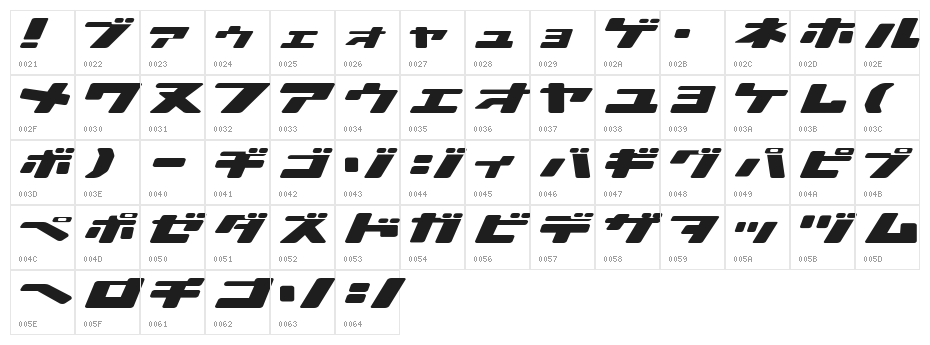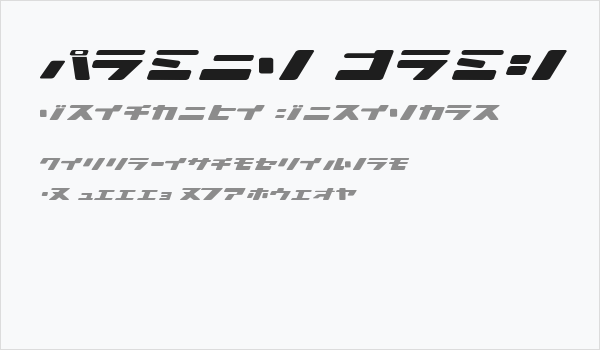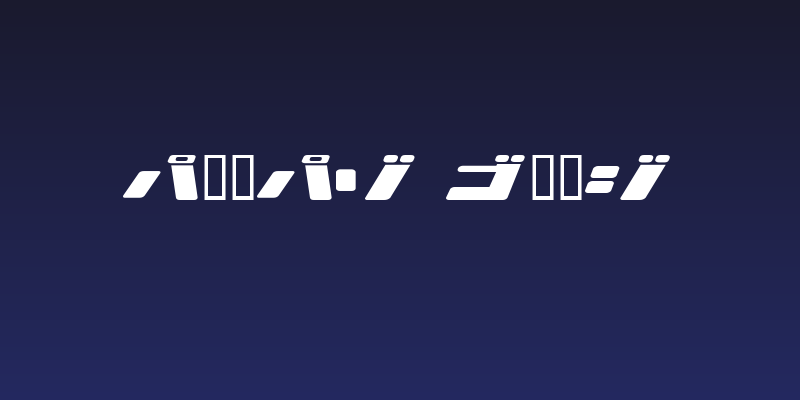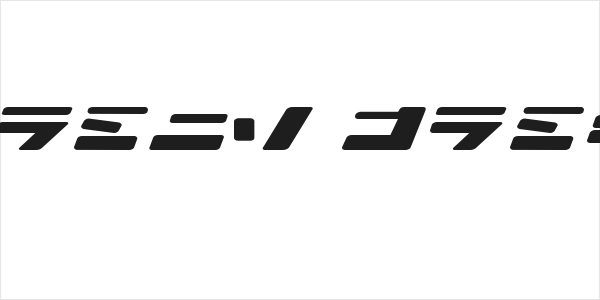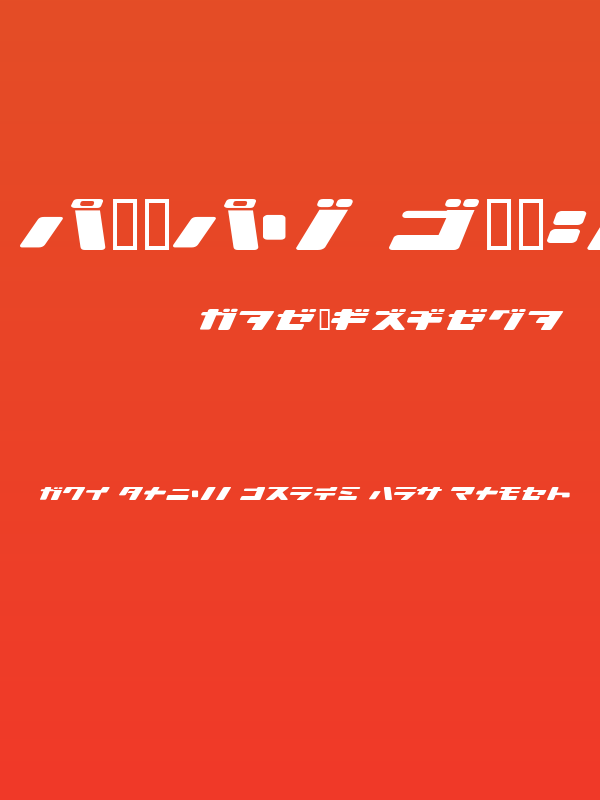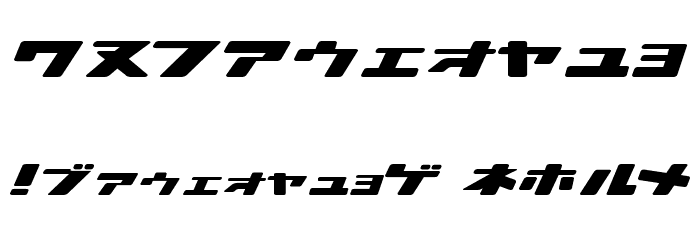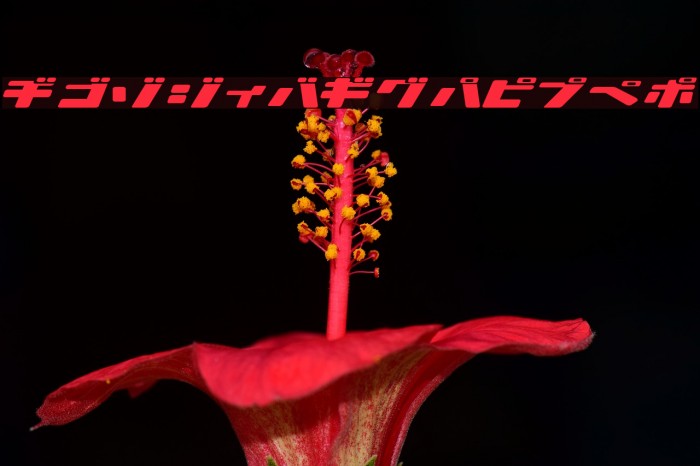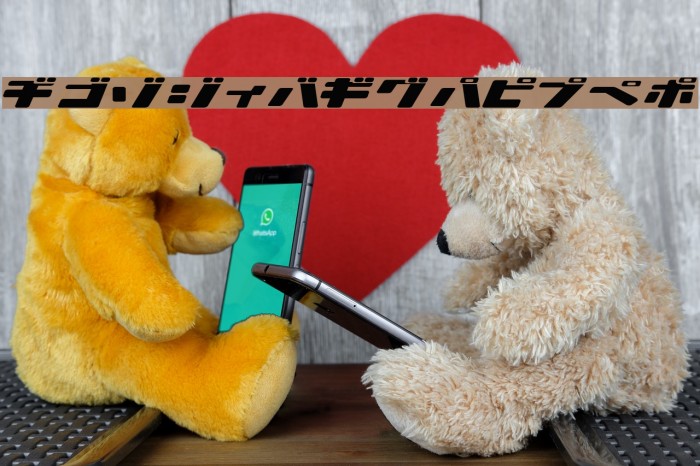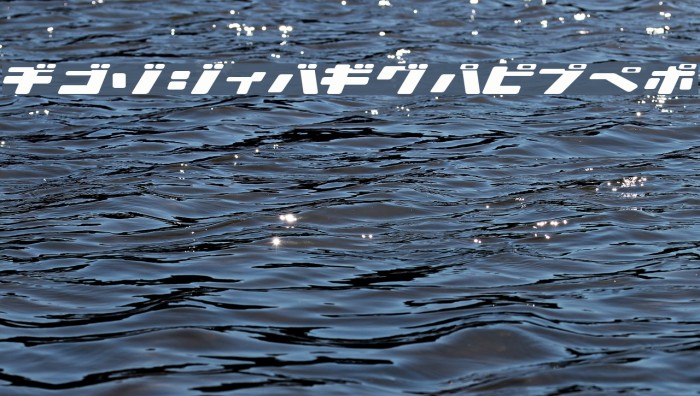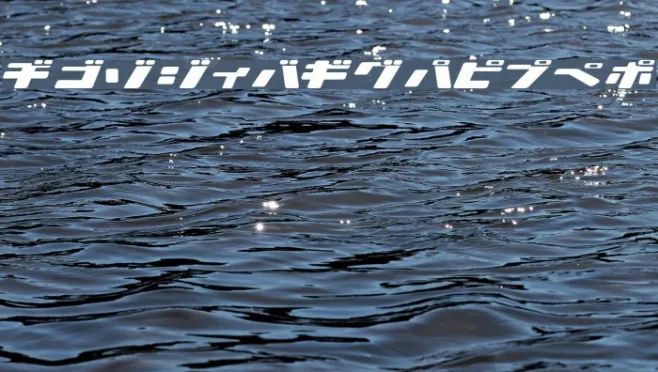
Ionic bond Font
✎ Futuristic
| Vorgeschlagene Projekte | Ideal for tech-related branding, sci-fi movie posters, video game titles, and sports team logos. |